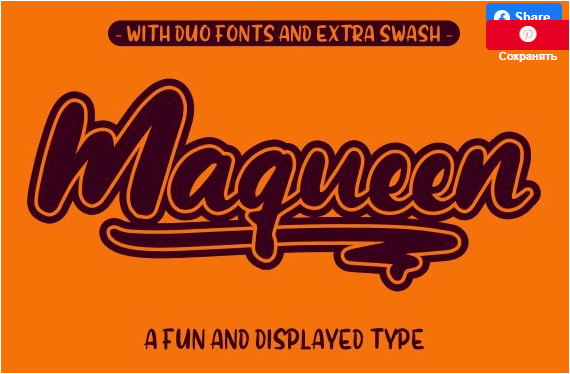
Maqueen Duo Font
Maqueen — это дружественный дуэт шрифтов. Он имеет закругленные углы и был вдохновлен семейными и забавными детскими вещами. Этот дуэт представлен в стиле display sans и в полускриптовом варианте, которые можно идеально сочетать друг с другом.
Вы можете использовать любой из включенных стилей в качестве основного, а остальные — для создания многослойной типографики с единой эстетикой.
Maqueen — это дружественный дуэт шрифтов. Он имеет закругленные углы и был вдохновлен семейными и забавными детскими вещами. Этот дуэт представлен в стиле display sans и в полускриптовом варианте, которые можно идеально сочетать друг с другом.
Вы можете использовать любой из включенных стилей в качестве основного, а остальные — для создания многослойной типографики с единой эстетикой.